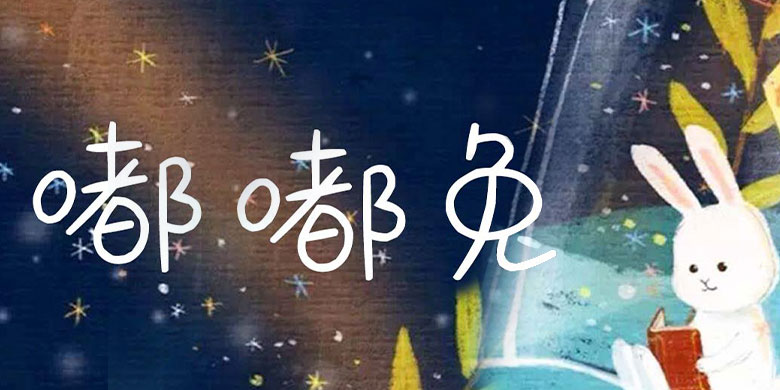
品牌:方正手迹设计师:余丹发行时间:2018字库编码:大陆简体(GB2312-80)分类:创意书写字体属性:精品字
一样的粗细,富有意趣的笔画,生动多变的结构,可爱的气质拿捏的恰到好处。整体笔画都是圆滑的,且采用较大的中宫,增加字面,具有良好的页面展示效果。适用于少年儿童类的书刊、品牌广告和产品包装设计,以及社交网络的个性化用字。